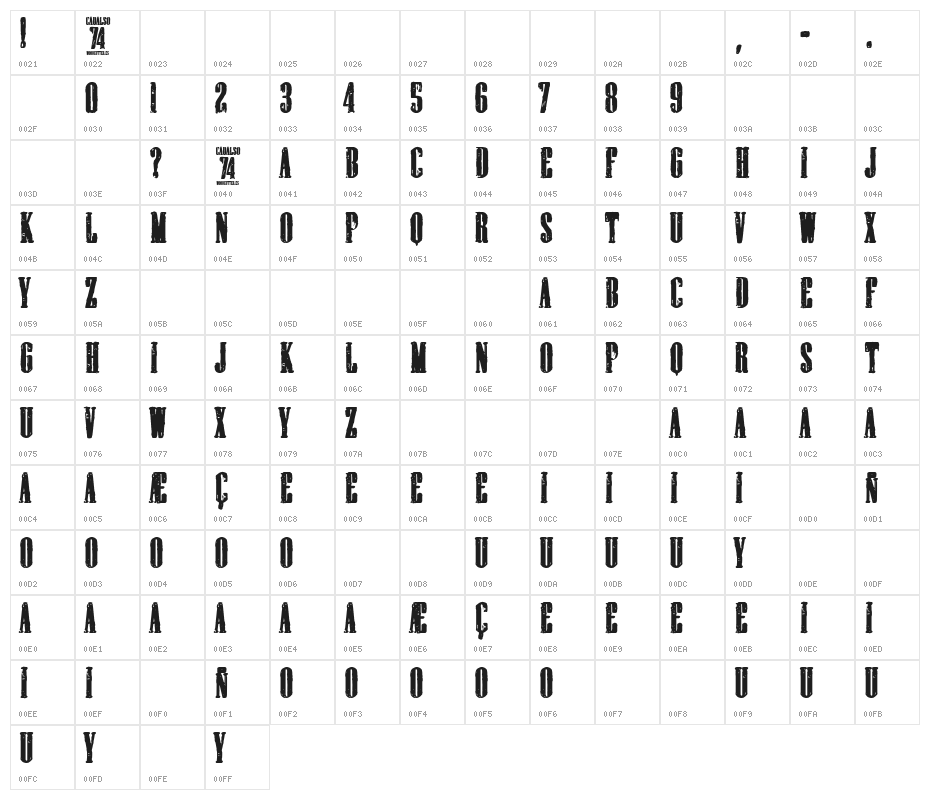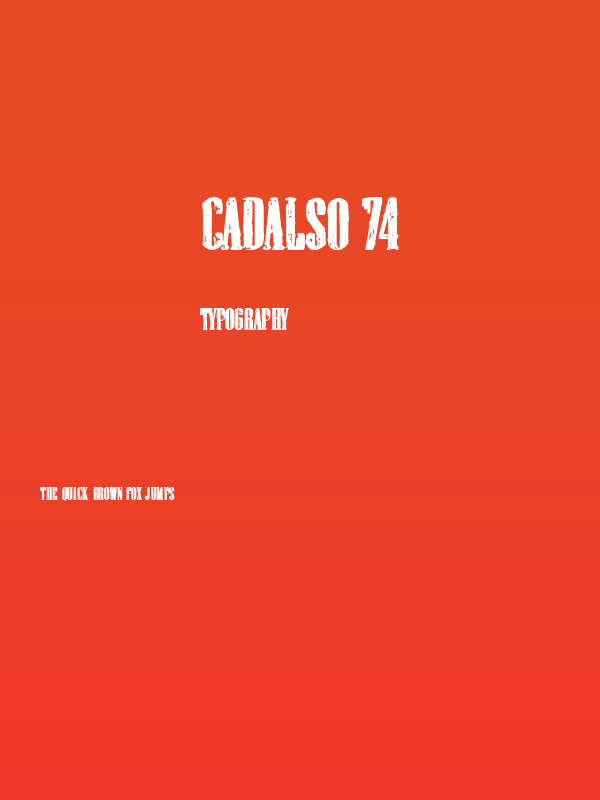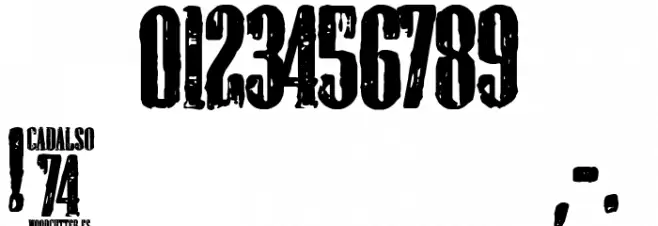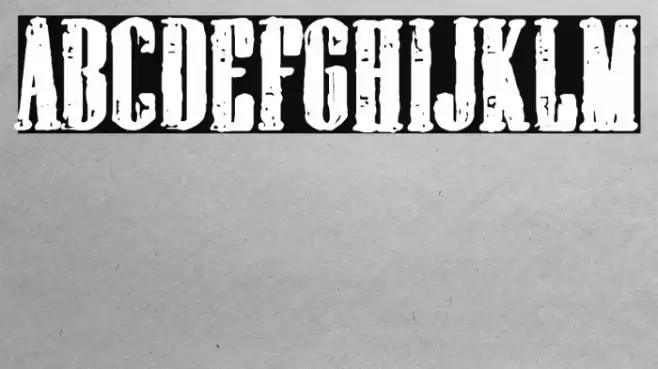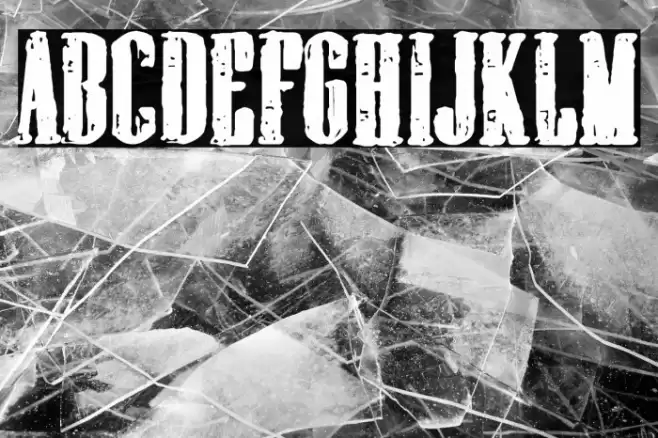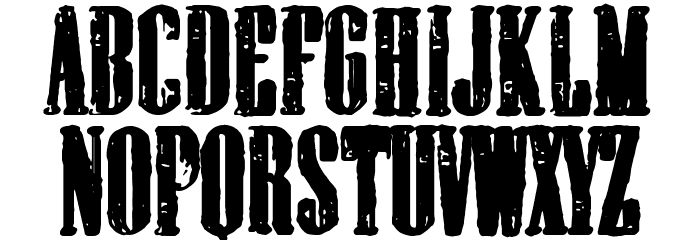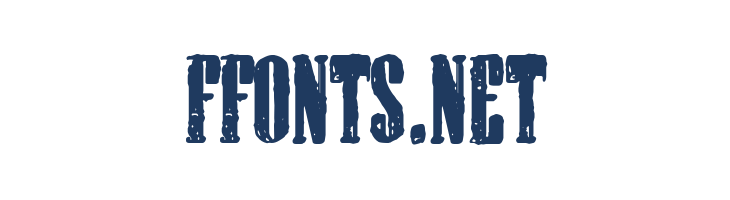
cadalso 74 Font
| Proiecte propuse | Ideal for posters, album covers, branding for rustic or industrial-themed products, and any design needing a bold, vintage impact. |